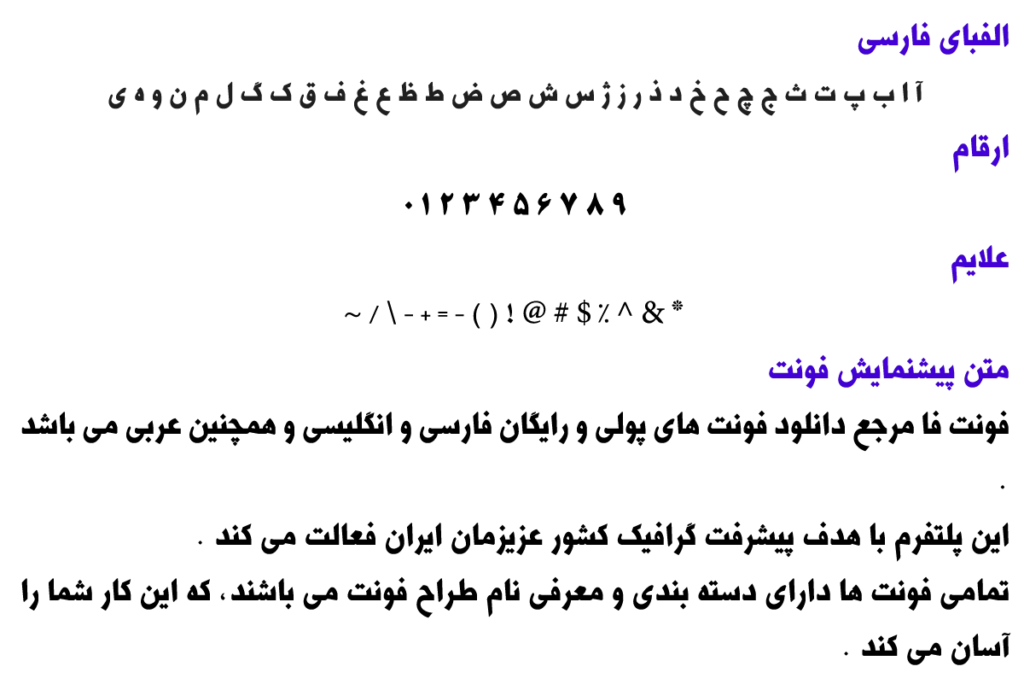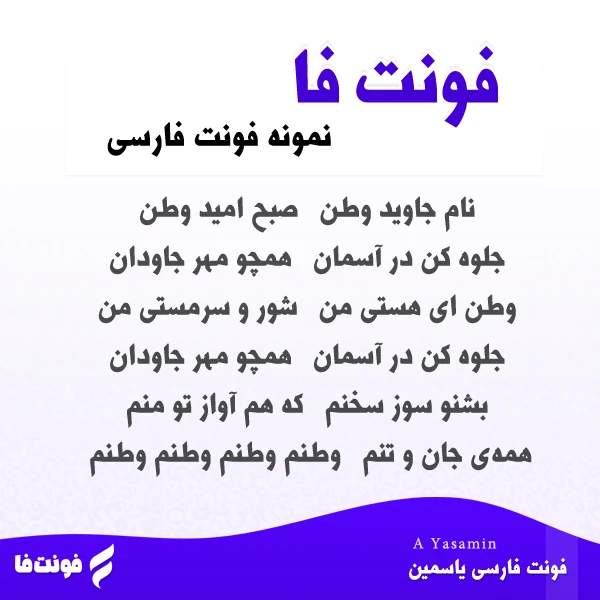
فونت فارسی یاسمین – A Yasamin
سال ساخت فونت: 1399
طراح فونت: امید کردی نوع فونت: فونت عنوان
پیشنمایش فونت یاسمین
توضیحات و معرفی فونت یاسمین
فونت فارسی یاسمین ( A Yasamin ) از مجموعه فونت های آزاد می باشد، و نیز نوع فونت عنوان می باشد.
فونت خوشگل مربوط توسط امید کردی در سال 1399 طراحی و ساخته شده است.
شایان ذکر است این فونت یکی از فونت های مریم سافت است که توسط طراح ویرایش و بازسازی شده است.
و نیز فونت Yasamin در یک وزن پر رنگ است.
در عکس زیر می توانید پیشنمایشی از تایپ فیس ببینید که توسط آن شعر زیبای وطن نگارش شده است.